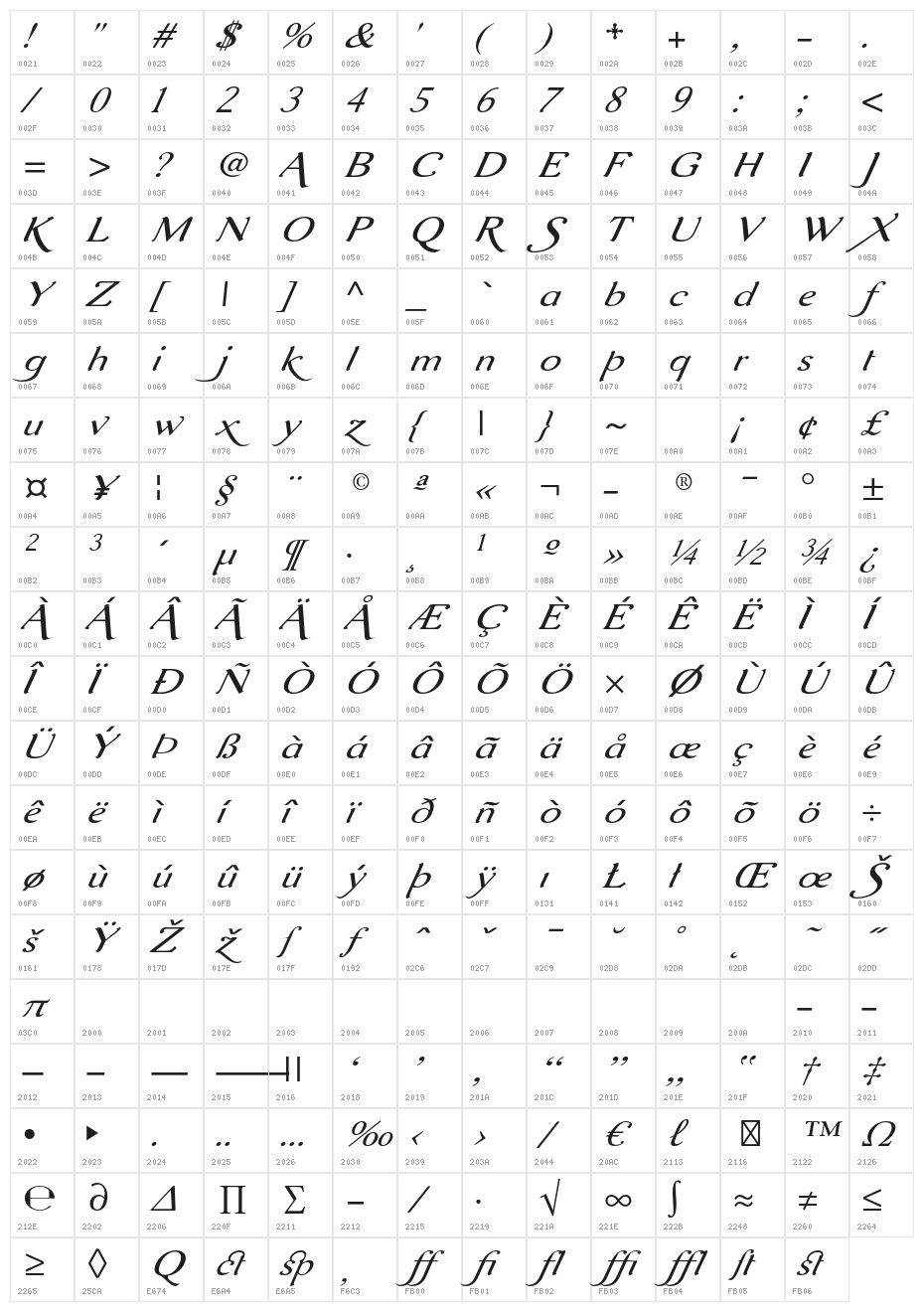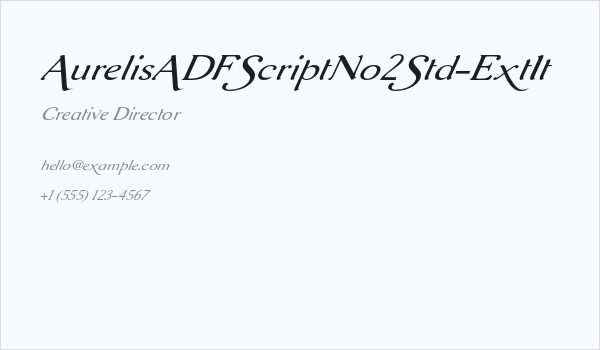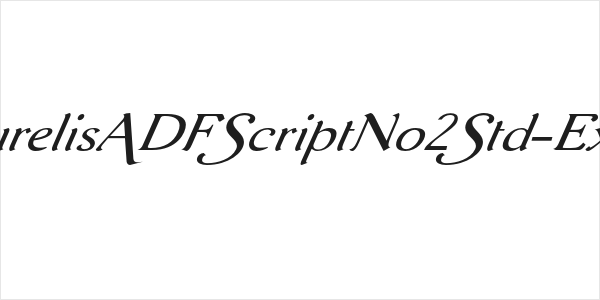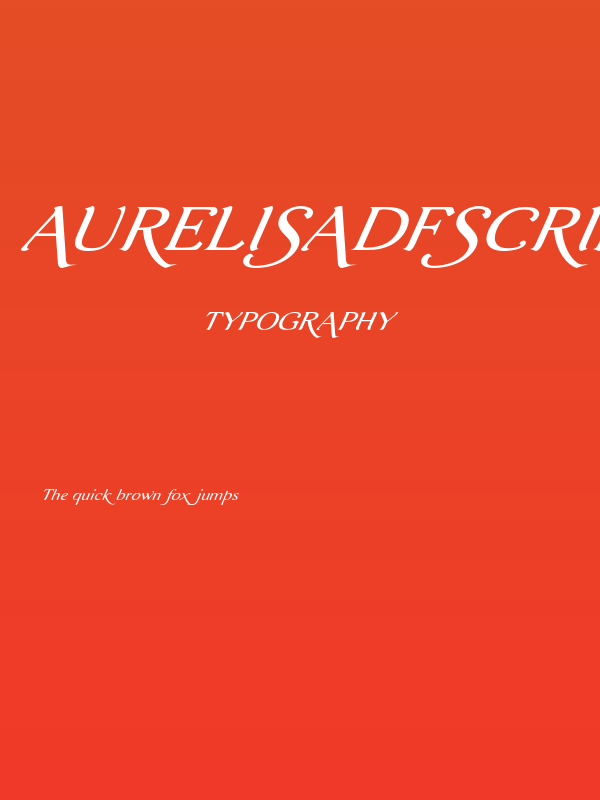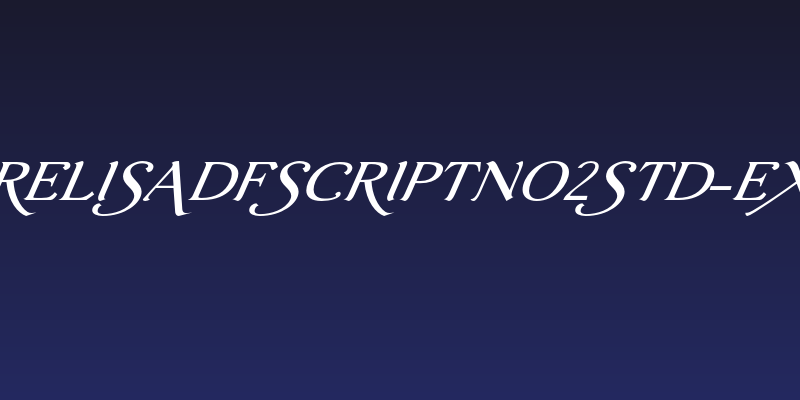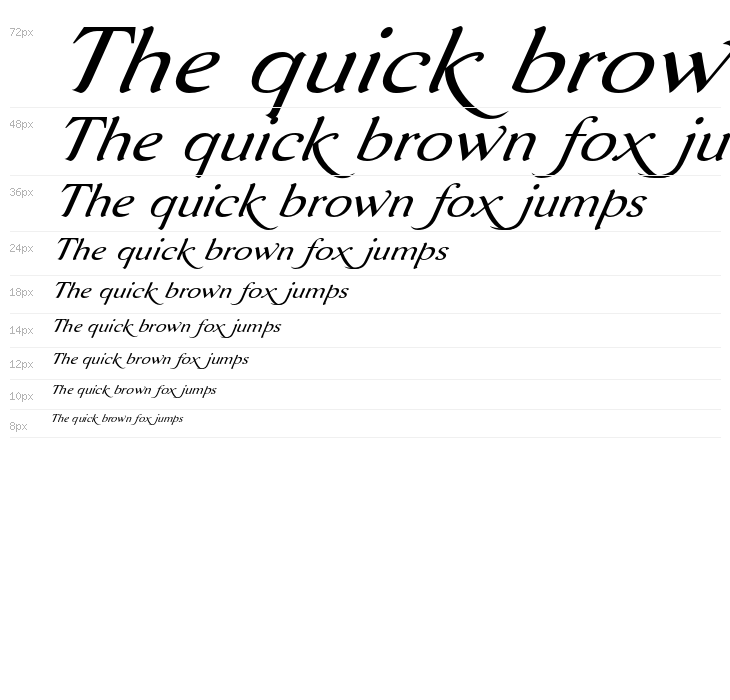
AurelisADFScriptNo2Std-ExtIt Font
| Stile generale | Elegant, Decorative |
| Caso d'uso | Invitations, Branding, Logos |
| Progetti proposti | Ideal for wedding invitations, elegant branding, greeting cards, and sophisticated logo designs. |